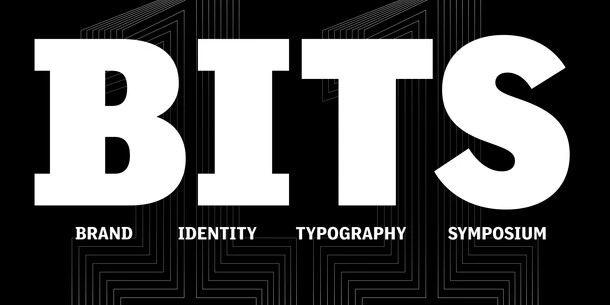
Monotype、東南アジアのタイポグラフィとタイプデザインに関するシンポジウム「BITS11」に参加
米国 Monotype Imaging Inc.の日本法人Monotype株式会社(東京都港区、以下 Monotype)は、2025年2⽉13⽇(⽊)から16⽇(日)までタイ・バンコクで開催される東南アジア唯⼀のタイポグラフィとタイプデザインのシンポジウム「BITS11」に、シニア・タイプデザイナー 土井遼太と中国のタイプデザイナー Tao Di(タオ・ディ)がスピーカーとして登壇いたします。
プレゼンテーションの内容
多言語サポートがますます重要になる中、CCJK(中国語、日本語、韓国語)の文字を扱う上での課題は依然として残っています。技術の進歩によって、大規模な文字セットを効率よくデザインできるようになってきましたが、完成度の面ではさらなる改善の余地があるでしょう。本プレゼンテーションでは、漢字のデザインに焦点を当て、CCJKの文字をデザインするのに役立つヒントをご紹介します。中国語や日本語を母国語としないデザイナーでも、漢字デザインの基本を学ぶことで、高品質なフォントを見極める力を身につけることができるようになります。フォントの制作だけでなく、評価の視点を養うことで、国際的なデザイナーとしてのスキル向上にもつながる内容です。
BITS とは
「BITS」とは、東南アジア、極東アジアの近隣諸国で活躍する書体デザイナーらが⼀堂に会し、アジア各国における書体やブランディングのトレンドについて、セミナーやワークショップを通して発信していきます。11回目となる今回は、東南アジアと世界のデザイン界との結びつきを強化すると同時に、業界との関係を向上させ、国際的な対話を促進することを目的としています。
Monotype シニア・タイプデザイナー 土井遼太
東京藝術大学デザイン科を卒業後、英国レディング大学書体デザインコースで修士号を取得。2015年よりタイプデザイナーとしてMonotypeに在籍し、企業制定書体の開発や、書体選定をはじめとしたコンサルティングを行う。また、たづがね角ゴシックの制作メンバーとして、ファミリー展開やCCJK言語に対応した字種拡張にも携わる。最近では、大学での講義や国際カンファレンスでの登壇を通じ、国内外に向けて書体についての発信をしている。
【これまで制作に携わった書体】
Shorai Sans
Avenir Nextの造形的要素を取り入れてデザインされたジオメトリック・サンセリフ体です。
たづがね角ゴシック
Neue Frutigerに合う日本語書体として開発された汎用性の高いヒューマニストサンセリフ体です。
Monotype タイプデザイナー Tao Di
Monotype 上海の書体デザイナー Tao Diは、大学では工学を専攻。卒業後はグラフィックデザイナーとして中国の広告代理店に就職。このときタイポグラフィに魅了され、独学で書体デザインを勉強する。Monotype入社以前は中国最大の書体ファウンドリー、方正字库のデザイナーとして、専用書体を含め数多くの書体の開発に携わる。
【これまで制作に携わった書体】
Shorai Sans
Garena Sea Group: GFF
Type Great Wall Motor Company Limited: GWM Sans